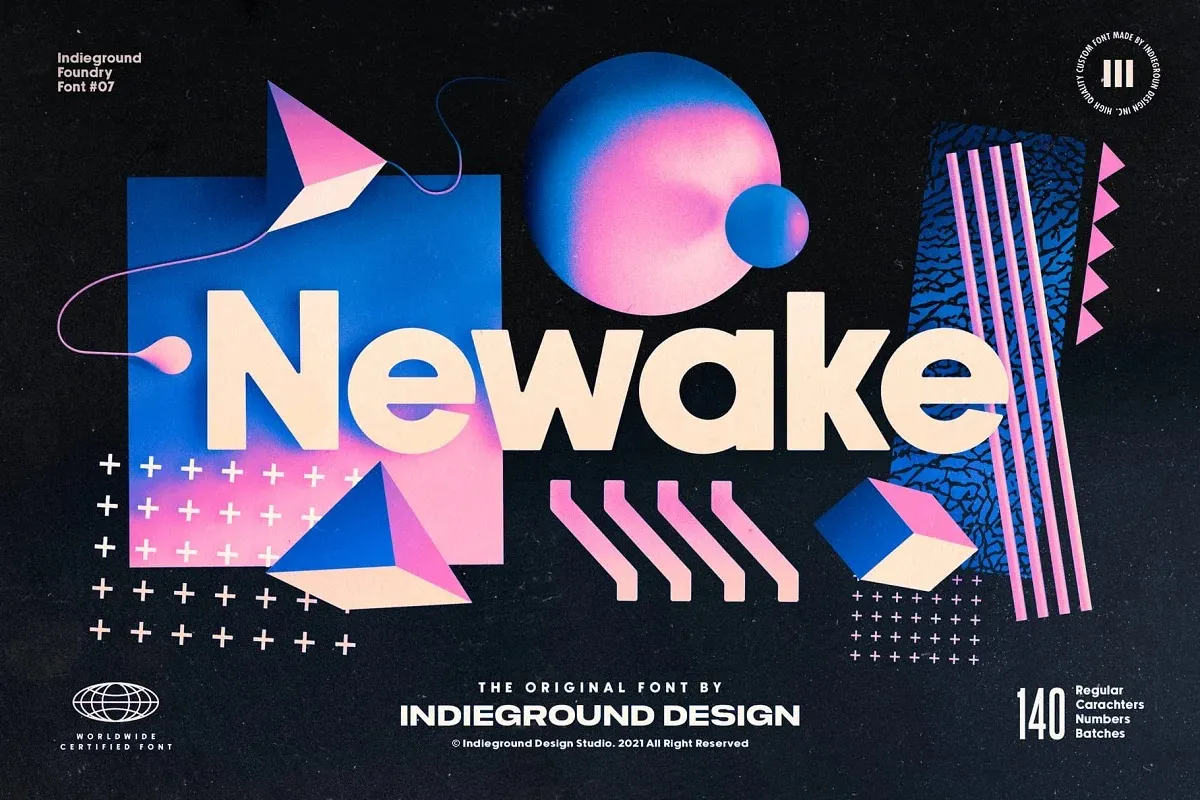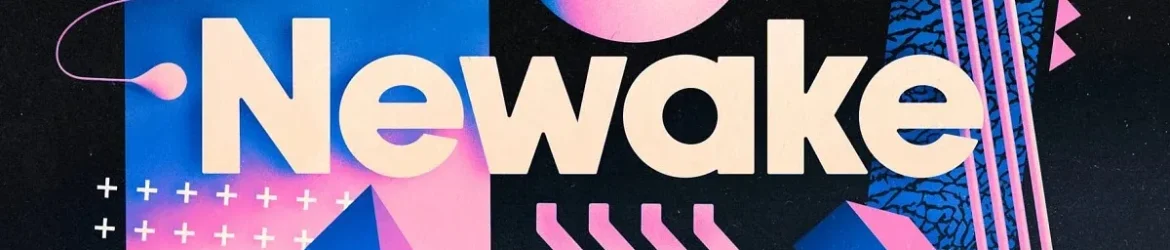
Esta fonte é uma tipografia sans-serif que mantém a elegância e a serenidade de qualquer projeto gráfico ou tipográfico. Com linhas arredondadas suaves nos cantos dos caracteres, ela dá um toque sofisticado aos textos e citações. Ideal para projetos artistas e designers digitais, esta versão comercial abrange o conjunto completo de caracteres disponíveis na pré-visualização. Com seu clima minimalista, ela adicionará uma sensação agradável e peso ao teu trabalho artístico. Esta fonte é perfeita para qualquer projeto que busque modernidade, elegância e um toque único em cada linha escrita.